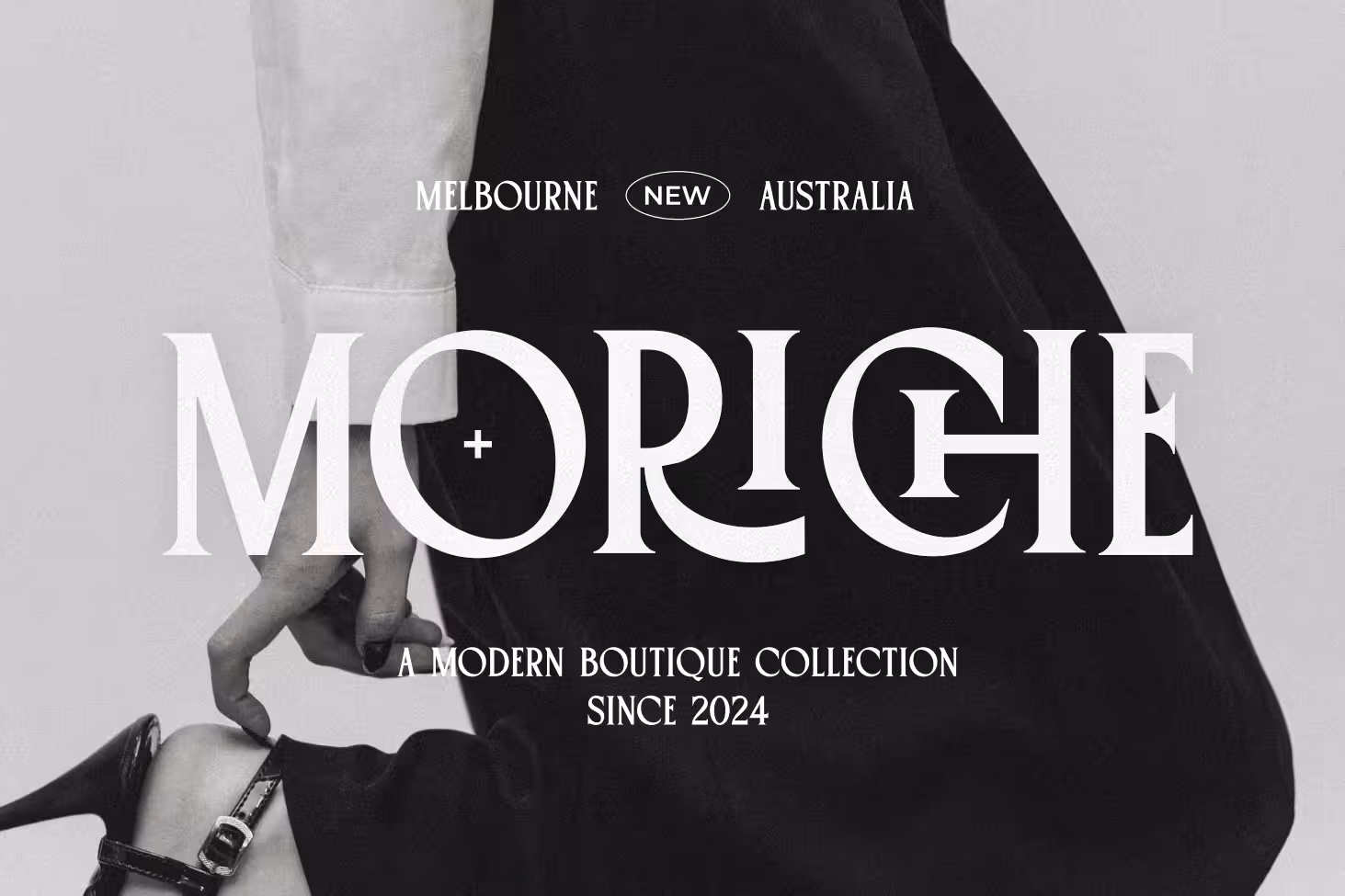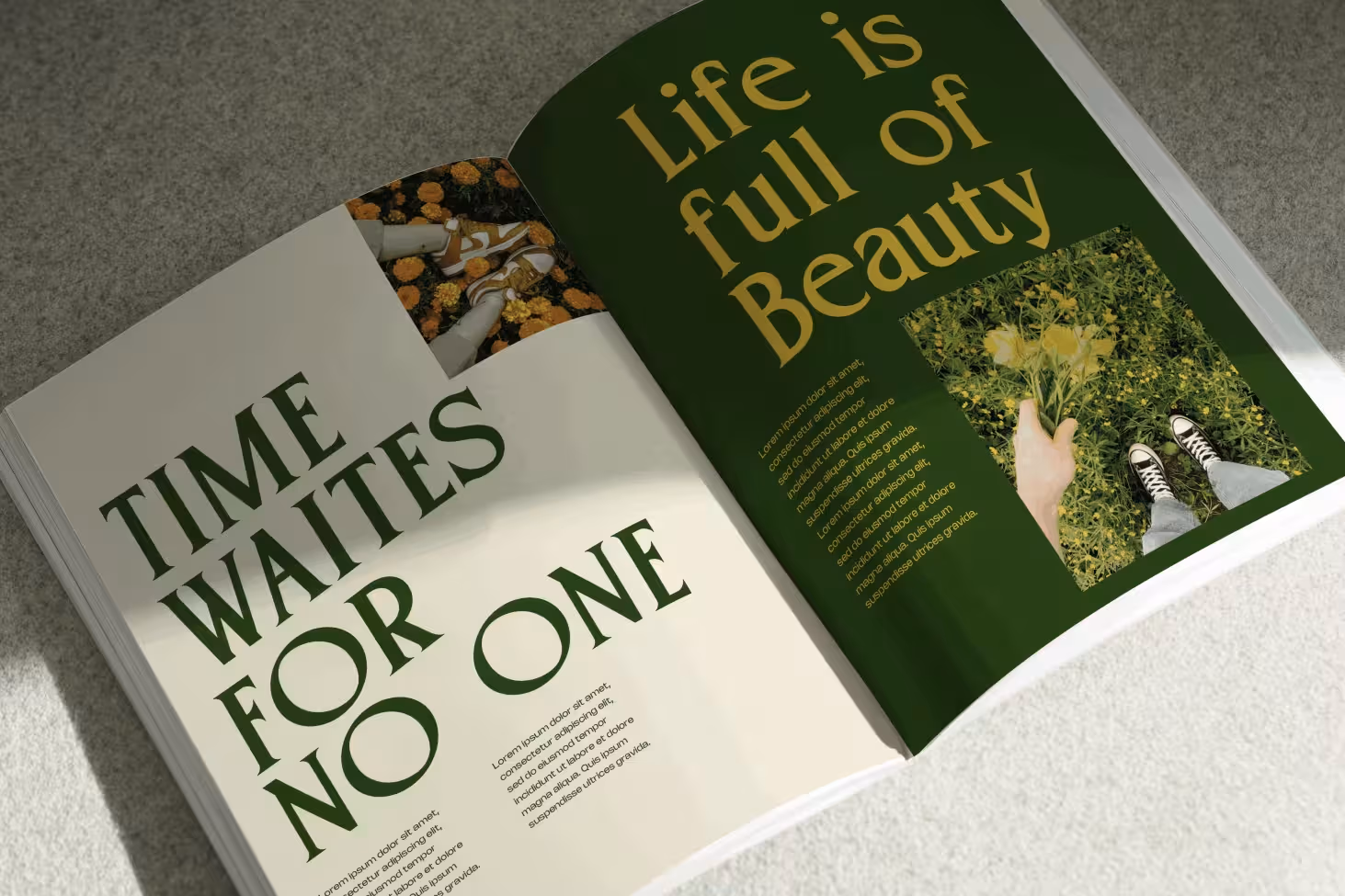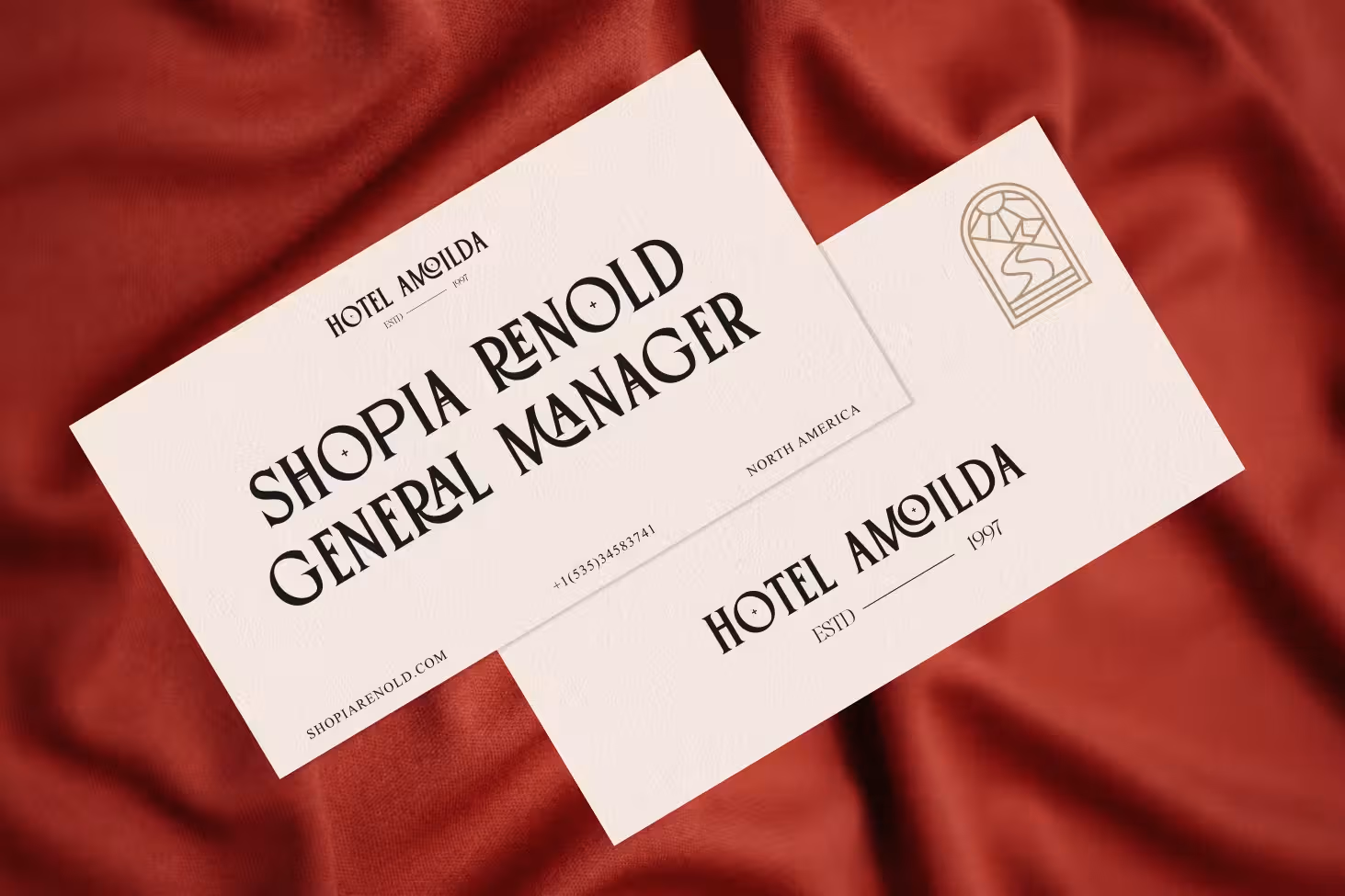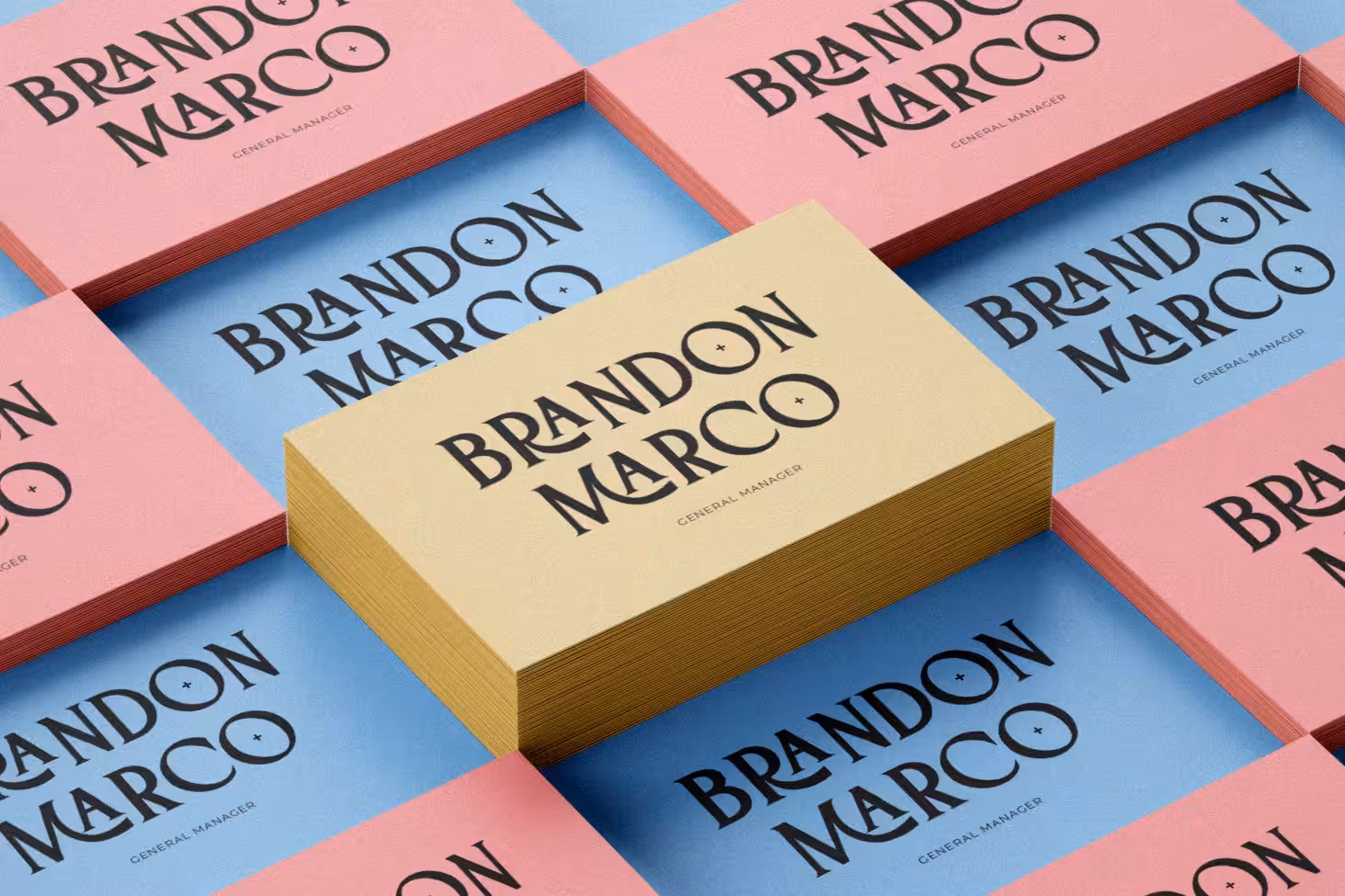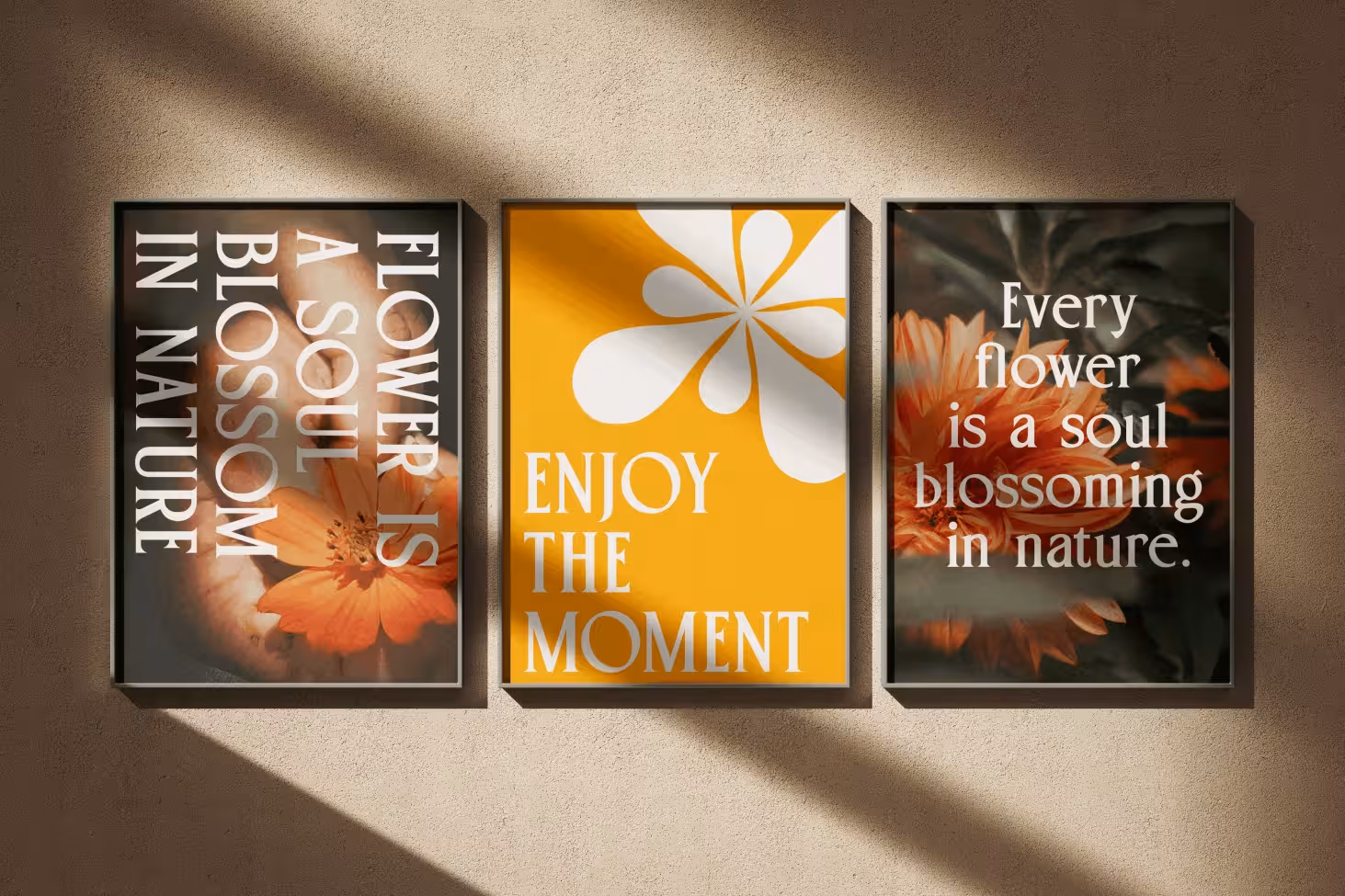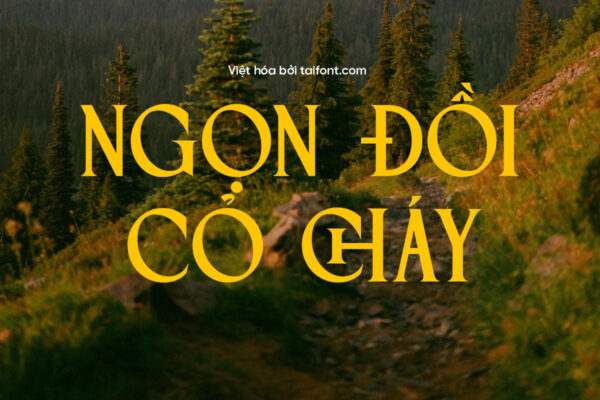
Giới thiệu về Font TF Gloriche Regular & Italic Việt hóa
TF Gloriche Việt hóa là một bộ font chữ có chân (serif) nổi bật với thiết kế siêu đẹp, tinh tế và đầy cuốn hút. Với hai phiên bản Regular (thẳng) và Italic (nghiêng), bộ font này mang đến sự linh hoạt trong việc thể hiện thông điệp, toát lên phong thái sang trọng, thanh lịch và cuốn hút đặc biệt. Đây là lựa chọn lý tưởng cho mọi ấn phẩm cần sự tinh xảo và đẳng cấp.
Với sự tinh xảo trong từng ký tự và tính thẩm mỹ vượt trội, Gloriche là lựa chọn hoàn hảo cho các thiết kế muốn truyền tải sự sang trọng và phong cách, đặc biệt là trong các lĩnh vực:
- Thiết kế tạp chí: Hoàn hảo để sử dụng cho các tiêu đề chính, lời dẫn, hoặc nội dung bài viết trong các tạp chí về thời trang, làm đẹp, lối sống cao cấp. Nét chữ có chân của font giúp tăng tính trang trọng và dễ đọc, đồng thời tạo cảm giác cao cấp, thu hút độc giả.
- Thiết kế nước hoa và mỹ phẩm: Lý tưởng cho các thương hiệu nước hoa, mỹ phẩm cao cấp, từ logo, nhãn mác sản phẩm, đến các bao bì và chiến dịch quảng bá. Font này giúp truyền tải vẻ đẹp thanh lịch, đẳng cấp và độc đáo của sản phẩm, nâng tầm giá trị thương hiệu.
- Thiết kế branding (nhận diện thương hiệu): Phù hợp cho logo, tagline hoặc bộ nhận diện thương hiệu của các công ty, doanh nghiệp muốn truyền tải sự tinh tế, uy tín và sự thanh lịch. Gloriche giúp xây dựng một hình ảnh thương hiệu vững chắc và dễ nhận diện.
- In ấn cao cấp: Đảm bảo khả năng đọc tốt trên giấy và tạo ấn tượng mạnh mẽ cho các ấn phẩm như brochure, catalogue, bao bì sản phẩm cao cấp, hoặc danh thiếp.
Với TF Gloriche Việt hóa, bạn có thể dễ dàng thổi hồn tinh tế, sang trọng và vẻ đẹp hoàn hảo vào các thiết kế, tạo ra những sản phẩm không chỉ đẹp mắt mà còn đầy cảm xúc và sức hút đặc biệt.